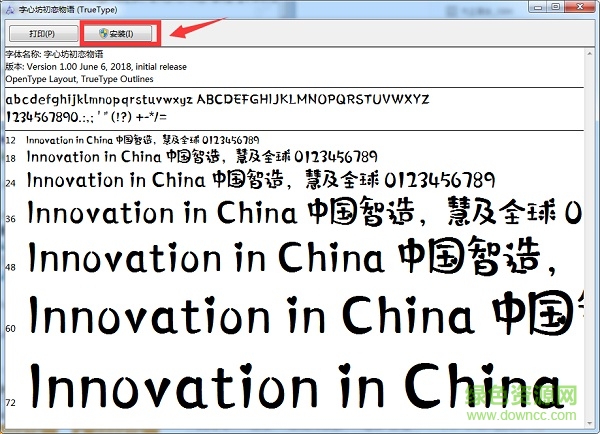
字心坊字體打包里包含了字心坊官方推出的所有字體資源。像大家比較喜歡的萌新體、初戀物語體、夢幻哥特體等等。后期小編也會繼續(xù)添加字心坊系列字體應用。喜歡的用戶不要錯過了哦!
字心坊童夢奇緣W
字心坊童夢奇緣W字體是一款調皮可愛的卡通字體,有靈動的俏皮感,筆畫圓潤,字體融入夢境般的風波卷元素,裝飾味十足,充滿童趣。字體個性鮮明,字形特點時尚新穎,性格乖巧,以俏皮多變的線條,造就一款蘊含童真、童夢的字體。讓我們乘著童年的時光機,進入奇妙的夢幻之旅,遇見一場奇緣。
字心坊童年體
字體童趣可愛,結構多變靈動,字形活潑清新,造型生動有趣,具有靈活的適用性,天真俏皮又不失時尚感。
字心坊小呀小布丁
該字體由一位古靈精怪的魔法少女創(chuàng)作而成。前期書寫過程能充分的反映出創(chuàng)作者心靈對于美好心境的詮釋。后經(jīng)電腦設計軟件進行修正、編輯,最后做成計算機字庫。字體風格新穎、可愛、個性、小清新、時尚、有趣,適用于標志、導視、書籍、游戲、動漫、影視、屏顯等方面。
字心坊夢幻哥特體
該字體是一款哥特風字體,字體獨特,新穎華麗。漢字藝術與西方文字的融合,如夜空中閃爍著暗黑光芒;個性鮮明的字體特征,散發(fā)著神秘而高冷的氣息。在華麗而不失婉約中,感受哥特風的魅力。
字心坊萌新體
字體萌動童趣,結構圓潤可愛,字形活潑清新,造型生動有趣,具有靈活的適用性,婉約俏皮又不失時尚感。
字心坊韻圓體
字體筆畫設計自然美觀,字形簡約,曲線優(yōu)美,優(yōu)雅圓潤,具有較大范圍的應用空間。字體個性鮮明,字形特點時尚新穎,同時融入古風結構,靈活多變的線條造就此款字體的與眾不同。
字心坊小令體
字體采用非襯線設計,字形融合中國小篆與黑體字的特點,取小篆的設計元素,同時力求精簡,簡化篆書,古為今用,在保證最大化識別度的基礎上,在變化中求得篆書之韻,盡顯古風之美。
字心坊詩雅體
字體采用非襯線設計,全部筆畫采用直線設計。字體個性鮮明,字形特點時尚新穎,同時融入古風結構,靈活多變的線條造就此款字體的與眾不同。字體風格新穎、時尚。